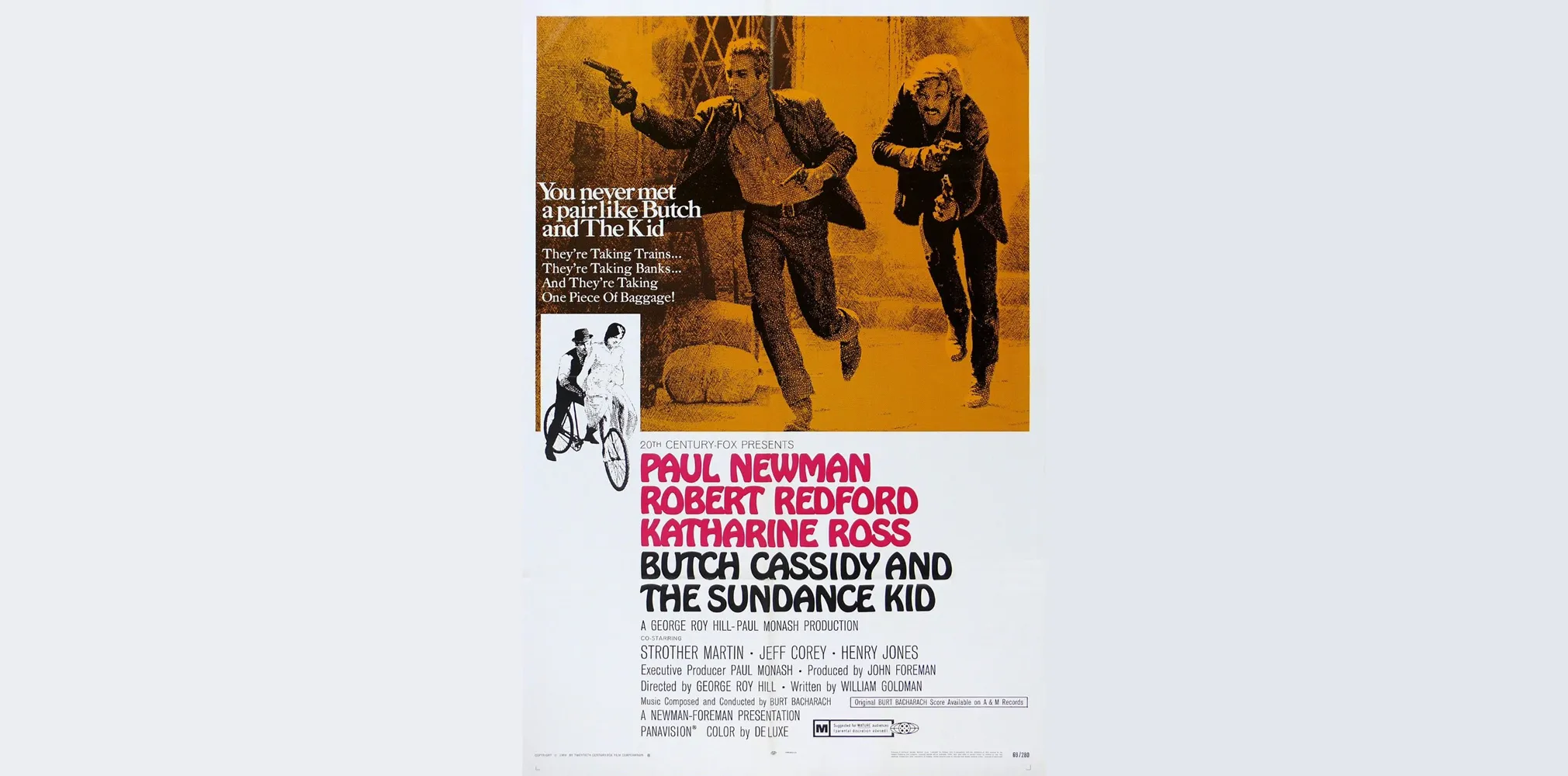
[Кино-шрифты: «Однажды в… Голливуде»] #1
Шрифт для фильма может не только отсылать на тон картины, но и содержать приятные пасхалки. В этом примере расскажу, как заморочился Тарантино.
Для фильма «Однажды в… Голливуде» были выбраны три основных шрифта.
Основная надпись — это смесь Hollywood Hills и ITC Machine. Первый придаёт надписи наклон отсылающий на надпись «Hollywood», а второй делает текст более стильным.
Шрифт для дополнительных надписей называется Hobo и он тоже выбран не случайно. Его использовали для промокампании многих фильмов выходивших в 1969, в год, когда происходят события Тарантиновской картины.
Вот, кстати, один из таких фильмов: «Буч Кэссиди и Сандэнс Кид» постер 1969 года.
[Кино-шрифты: «Однажды в… Голливуде»] #2